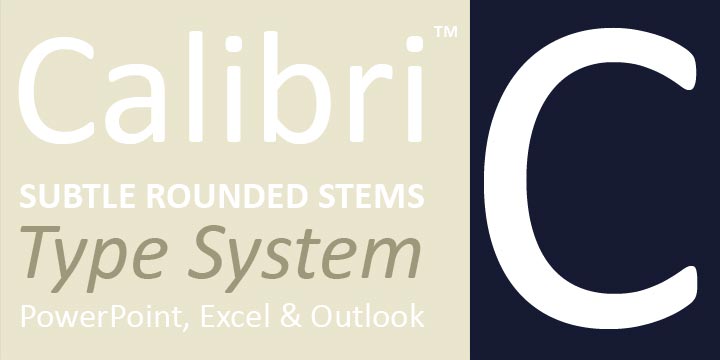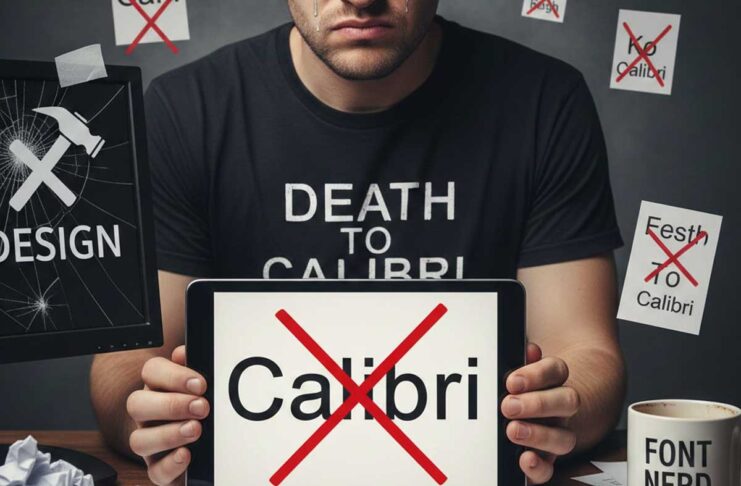
L’amministrazione Trump prende di mira il font Calibri, considerato “troppo inclusivo, radicale e uno spreco”. Il segretario di Stato, Marco Rubio, ha ordinato ai diplomatici di eliminare il font “sans serif” (ovvero, senza grazie) in questione usato nelle comunicazioni del Dipartimento di Stato, e di usare solo il Times New Roman (un font con grazie), ritenuto “più formale e professionale”.
In realtà il Calibri era stato voluto nel 2023 dall’amministrazione Biden perché più leggibile per chi ha problemi alla vista e per le persone con dislessia; quest’ultimo è molto conosciuto perché per anni è stato il carattere di default di proposto da Office, sostituendo i precedenti default Times New Roman (per Microsoft Word) e Arial (per PowerPoint, Excel e Outlook). Dal 2023 Office propone come font di default Aptos, altro font san serif (senza grazie) ispirato “alla tipografia svizzera della metà del XX secolo”.
Anche i font dunque rientrano nella lotta di Trump contro le politiche pro-diversità e inclusione. Nell’ordine inviato al Dipartimento di Stato e diffuso dal New York Times, il Segretario di Stato definisce il carattere che era stato scelto dall’amministrazione Biden come un regalo “dispendioso” alla diversità.
Per Rubio, l’introduzione del Calibri obbliga programmi “radicali” di diversità, equità, inclusione e accessibilità, mentre il Times New Roman permetterà di “ripristinare il decoro e la professionalità nel lavoro scritto del Dipartimento”.
Una curiosità: nel 2017 il Primo Ministro pakistano fu costretto alle dimissioni dopo avere individuato compromettenti documenti retrodatati. Erano palesemente falsi, anche perché il font Calibri usato per redigere i documenti all’epoca non esisteva.